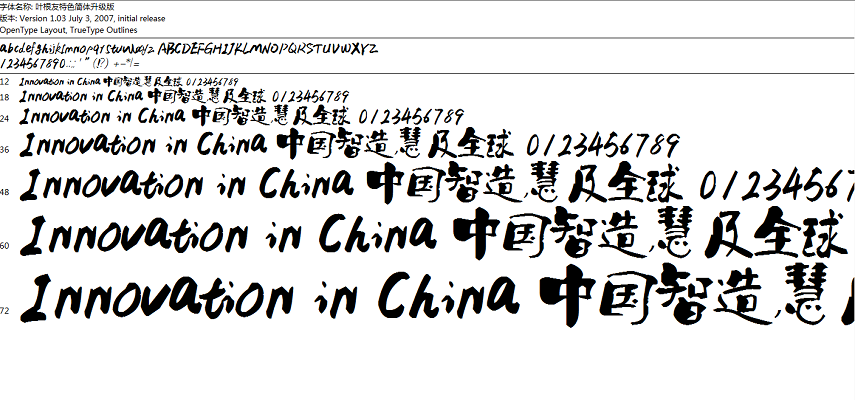
葉根友特色簡(jiǎn)體升級(jí)版對(duì)之前的特色簡(jiǎn)體進(jìn)行了升級(jí),在打破傳統(tǒng)毛筆書法寫法的基礎(chǔ)上,更加凸顯了自己的特色,極具創(chuàng)意和想象力,喜歡這款字體的朋友們快來綠色資源網(wǎng)下載體驗(yàn)吧!
葉根友毛筆特色簡(jiǎn)體是由中國(guó)書法奇人葉根友先生親自書寫的獨(dú)特創(chuàng)意的一款字體,該字體特色明顯,打破傳統(tǒng)毛筆書法寫法,自創(chuàng)一派.